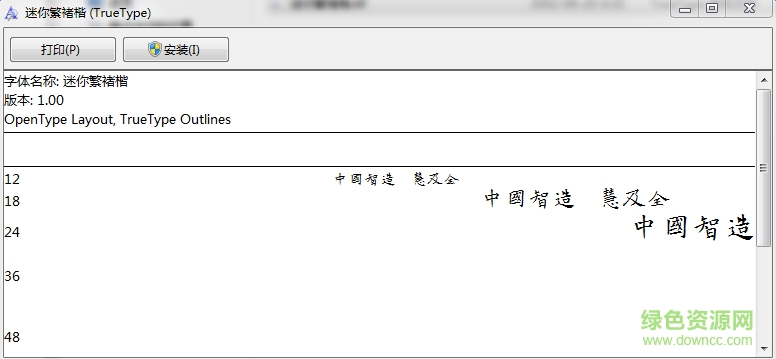
fzukai
fzukai字体又叫迷你繁褚楷,是一款细劲有力的楷书字体,该字体结构精到,点画清楚,洒脱美观,不过这款字体有少数字无法显示,需要的朋友快来下载吧!
四大楷书介绍
柳公权——柳体
柳公权的楷书参有欧阳询的笔法,往往将部分笔画紧密穿插,使宽绰处特别开阔,笔画细劲,棱角峻厉,虽用笔出自颜真卿,而与颜真卿的浑厚宽博不同,特别显得英气逼人。
欧阳询——欧体
以楷书和行书著称。为书法史上第一大楷书家,其字体被称为“欧体”,与颜(真卿)体,柳(公权)体,赵(孟頫)体并驾齐驱。
柳公权——柳体
柳公权所写楷书,体势劲媚,骨力道健。较之颜体,柳字则稍清瘦,故有“颜筋柳骨”之称。
颜真卿——颜体
颜的楷书,反映出一种盛世风貌,气宇轩昂;而他的行草,使宋代米芾也心仪斯书,原因是那些书帖往往是在极度悲愤的心境中走笔疾书的,读者可从本文中领略个中滋味。